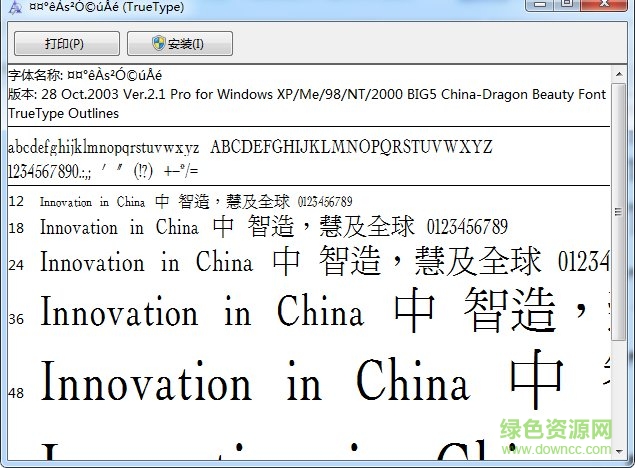
中國龍細(xì)明體繁是一款個(gè)性化的繁體字。這款字體擁有細(xì)明體所有特點(diǎn),使用的是中國傳統(tǒng)的繁體字,適合要用到各種字體做設(shè)計(jì)的朋友,歡迎用戶來綠色資源網(wǎng)下載安裝使用。
細(xì)明體是 Microsoft Windows 中文版內(nèi)附的中文字型,由華康科技(今名“威鋒數(shù)位”)所制作。當(dāng)使用于不能顯示中文字型名稱的系統(tǒng)時(shí),會(huì)顯示為MingLiU。細(xì)明體原來內(nèi)附的 ASCII 字符為等寬字體,當(dāng)用于顯示英文內(nèi)容(如中英文混合的網(wǎng)頁)時(shí)會(huì)不大美觀,于是后來推出了新細(xì)明體(PMingLiU),當(dāng)中的 ASCII 字符改為比例字體,但中文部份則一樣,并以 TTC 技術(shù)包裹于同一檔案 mingliu.ttc 中。細(xì)明體至Windows 2000 開始同時(shí)支援 Unicode,并提供 Unicode 1.1 版本內(nèi)所有 T-Source (臺(tái)灣字源)的字;及后 Windows XP則提供所有繁簡漢字。